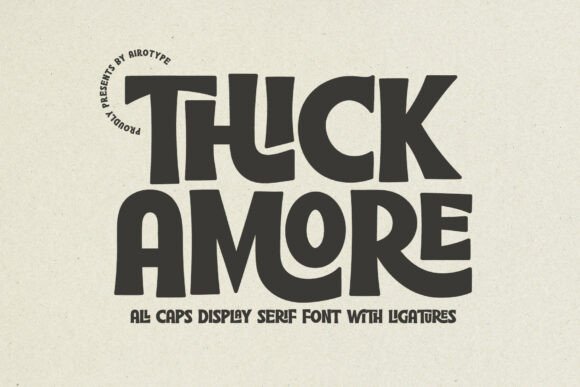
Thick Amore
適切なデザイン要素を見つけるのは難しい場合がありますが、Thick Amoreは作品を即座に引き立てる優れたコレクションを提供します。
POD(オンデマンド印刷)製品、結婚式の招待状、またはソーシャルメディアのグラフィックを作成している場合でも、Thick Amoreは理想的です。